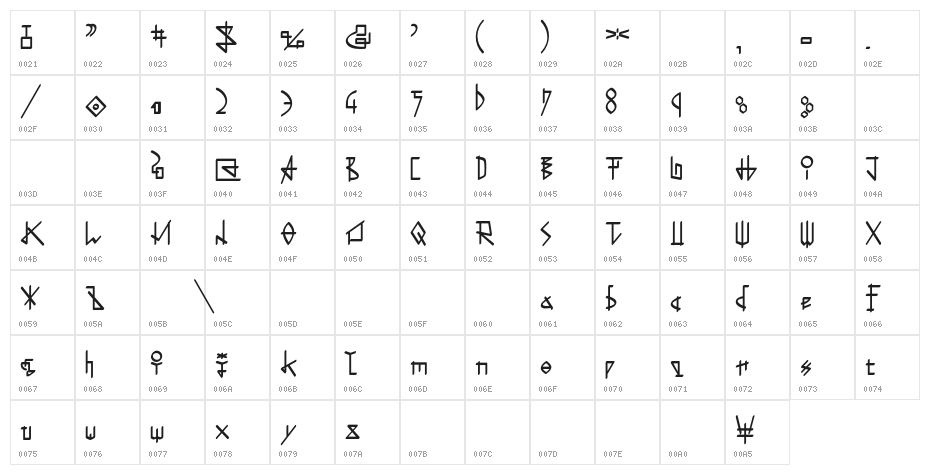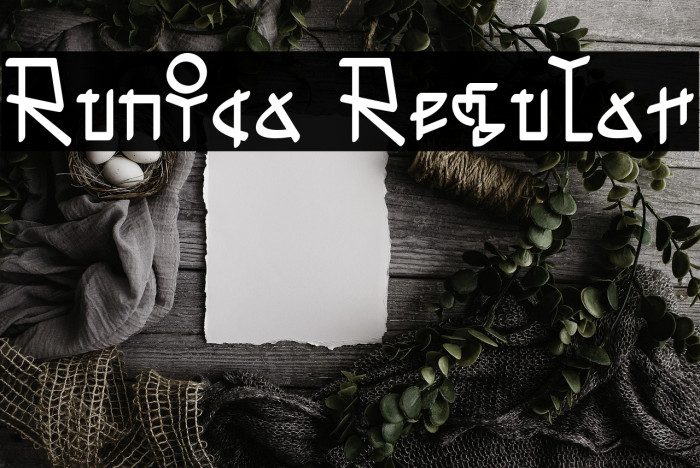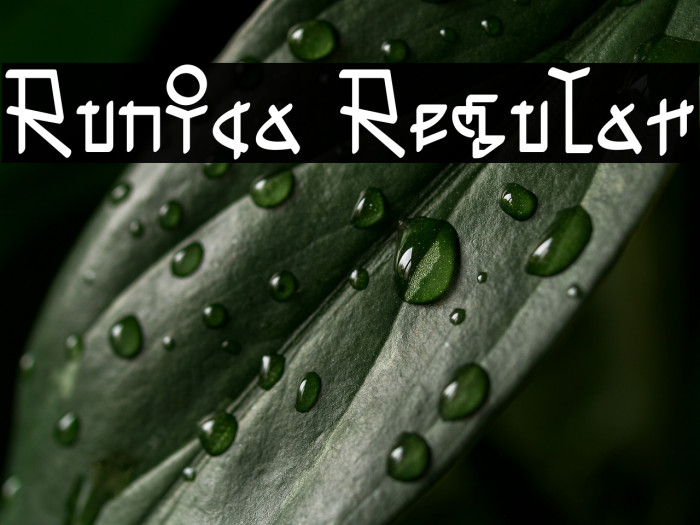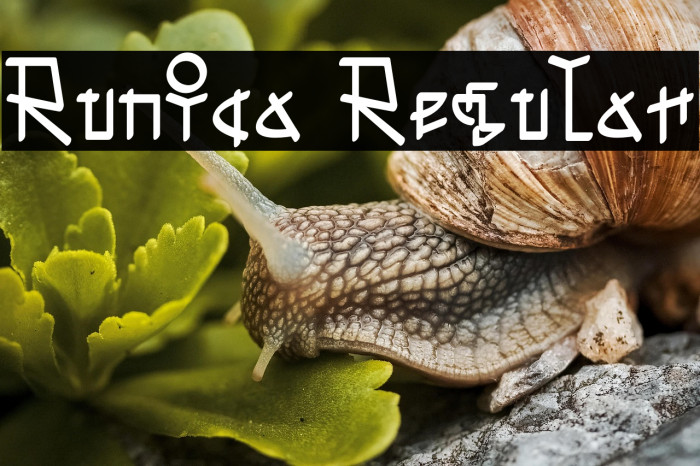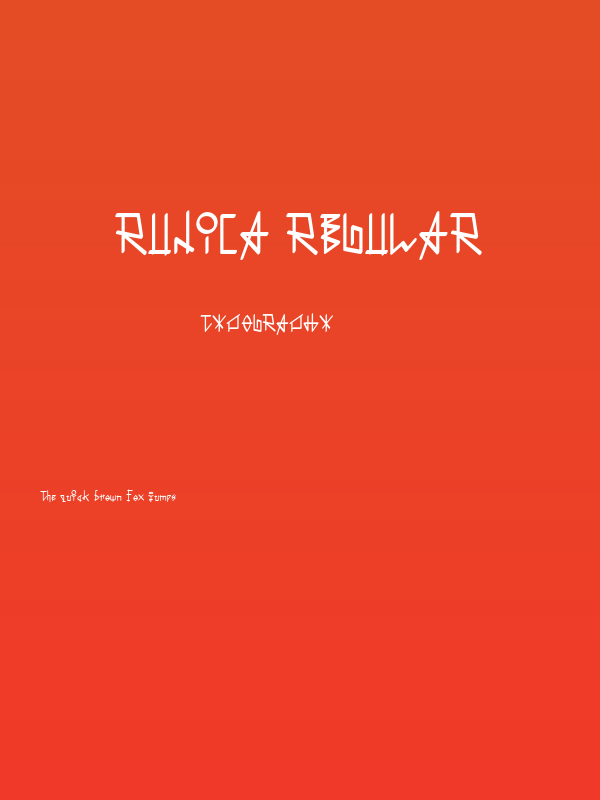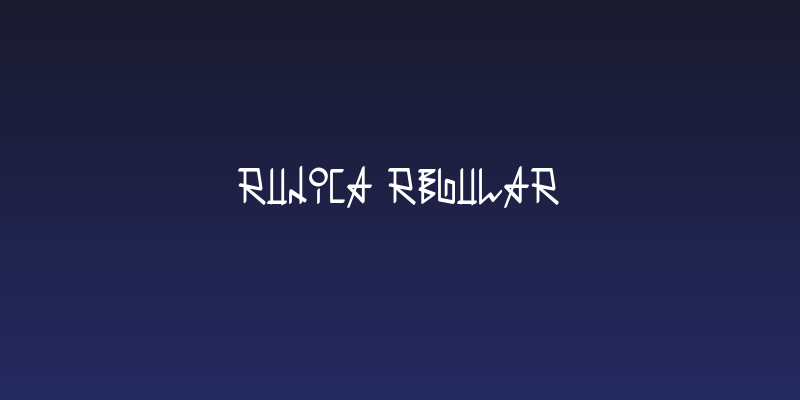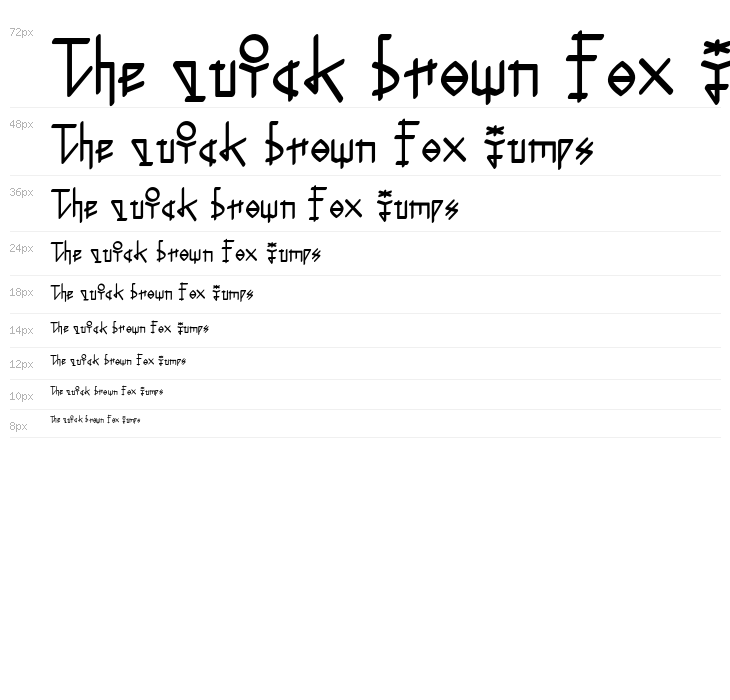
Runica Regular Font
| Caso d'uso | Logos, Posters, Themed Events |
| Progetti proposti | Ideal for fantasy-themed projects, historical recreations, video game design, or any creative work requiring an ancient or mystical aesthetic. |